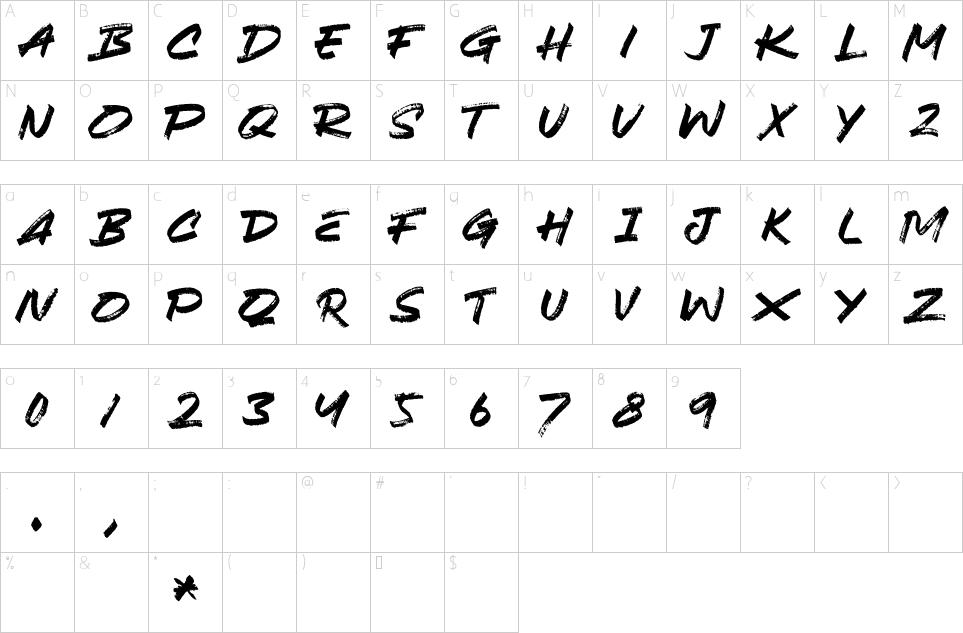
Descubra a riqueza das letras com Dekanova Font, uma fonte de graça que transforma qualquer texto em um verdadeiro trabalho de arte. Desenvolvida pela Lettermine, esta elegante e sofisticada fonte é ideal para quem procura um equilíbrio perfeito entre força e delicadeza. Possui uma arquitetura fluida que permite adaptar-se facilmente a diversos usos, desde o design gráfico até a produção de letras para impressão digital. O download da Dekanova Font foi baixado 886 vezes, demonstrando seu valor para designers, ilustradores e pessoas que buscam qualidade sem sacrificar o prazer. Seja você um profissional ou uma pessoa comum buscando uma maneira única de expressar sua visão através do texto, a fonte Dekanova está aqui para fazer isso mais facilmente. Em contraste com muitas outras opções de fontes gratuitas que podem parecer frágeis ou exageradas, a Lettermine trouxe um padrão sólido e confiável à sua disposição. Descubra por si mesmo o encanto dessa fonte em seu próximo projeto. Não hesite em experimentar a Dekanova para ver como ela pode transformar o simples texto em uma obra de arte.